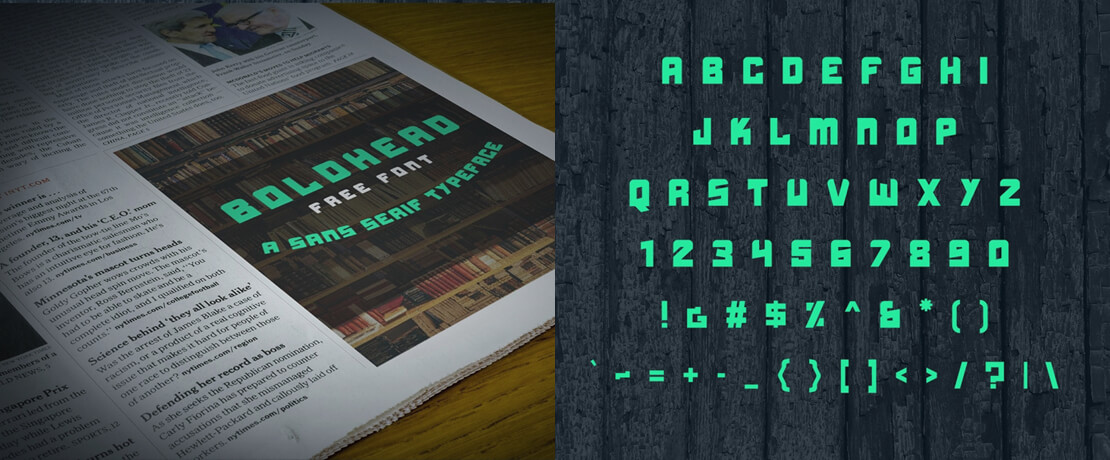
Boldhead
Boldhead ist ein Free Font vom bangladeschischen Designer Rakib Mostafiz. Die Schriftart steht kostenlos im Opentype-Format zum Download bereit.
Der Designer sieht die Einsatzgebiete des Display-Fonts in Bereichen wie Logo-Design, Branding, Anzeigen-Design, Marketing und mehr. Zur Auswahl stehen drei Download-Links. Diese werden auf der behance.net-Seite zum Font-Projekt aufgeführt.